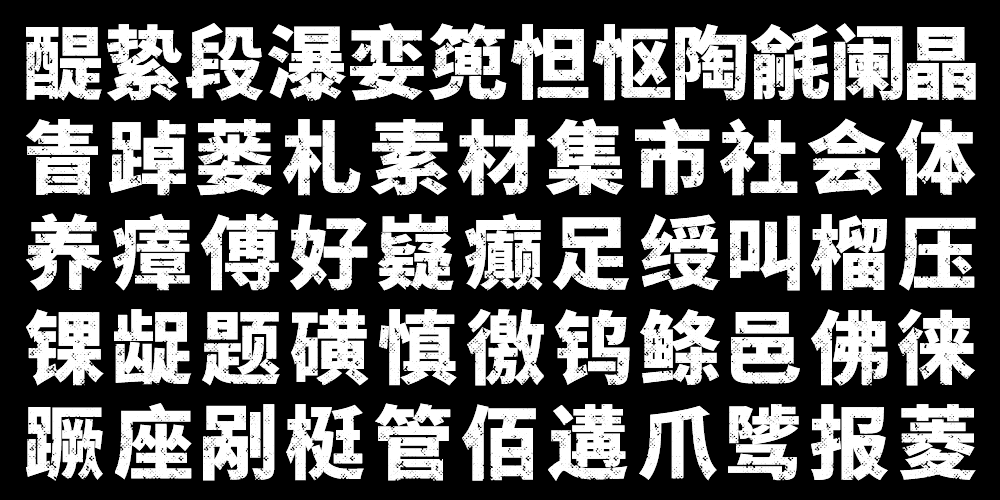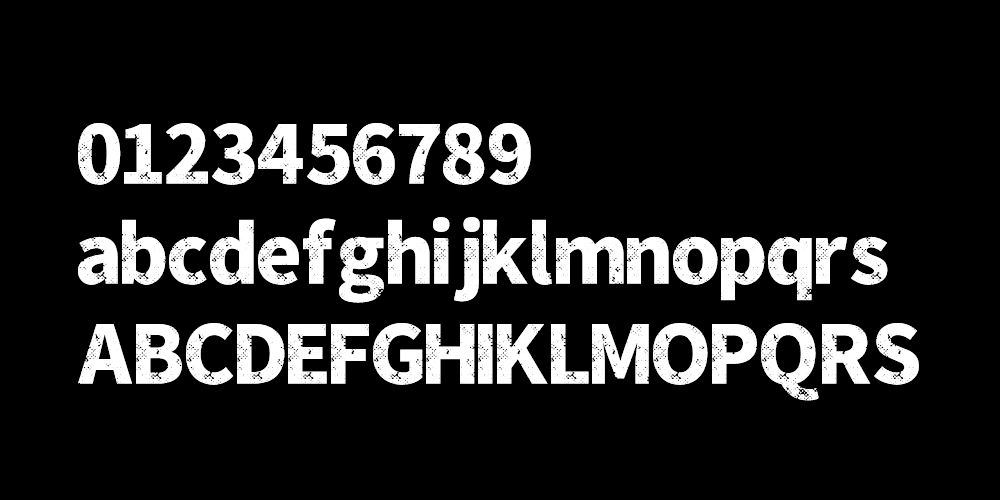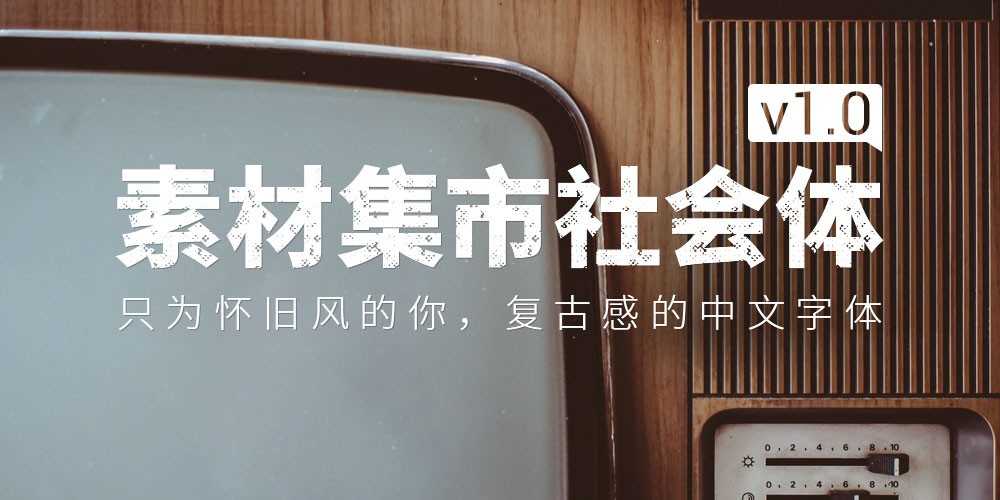
在五一来临之际,迎来了素材集市第四款原创字体「社会体」,由10名字集成员近4个月时间联合制作完成。作为各行业设计师,跨界完成一套字库,实属不易,感谢大伙的配合和支持。
字体简介
一款基于思源黑体-Black字型上创建的字体,在不破坏原有字型的基础上,添加了破旧斑驳效果,独特的破旧字型充满复古怀旧风。字涵盖国家GB2312编码标准的6763个简体中文,加上英文、数字和符号共6888个字符。
后续版本由字客网团队优化补充
- 调整字间距
Ver 3.00(2021/04/30)
- 素材集市社会体更新至3.0版本,字数6888字
Ver 2.01(2021/04/28)
- 素材集市社会体更新至2.1版本,字数4409字
Ver 2.00(2021/04/24)
- 素材集市社会体更新至2.0版本,增加至4409个字。
Ver 1.00(2021/04/09)
- 素材集市社会体增加至1071个字。
Ver demo(2021/01/25)
- 素材集市社会体发布Demo版本。
输入“勿”会显示“错”,能修复一下吗?打不出“勿”字
这个好,再用一些笔刷点缀下能省很多功夫
就这要10个人4个月?fontlab十分钟产出。
你说的没错,当初做字体是AI软件一个一个制作校对的,利用空余休息时间搞得,所以才有4个月
有点粉笔写出来斑驳的感觉,很赞。